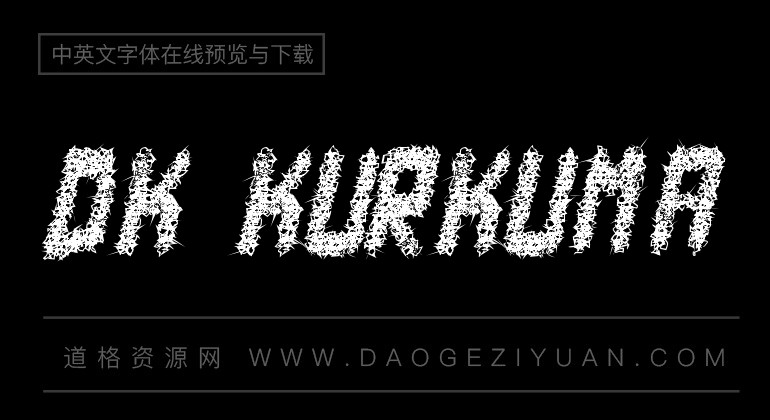
DK Kurkuma
? DK Kurkuma 是一款源自印度的抽象笔画字体,由设计师 Dinesh Kumar 创作。字体的特点是抽象的笔画,结合了中国的山水画和印度的图腾图案,给人以深刻的印象。字体采用了精细的细节设计,使用了鲜艳的色彩,给人以时尚现代的感觉。它具有良好的可读性、优美的外形和丰富的表现力,可以用于设计海报、书籍封面、网站标志、广告牌等。
DK Kurkuma是一款非常不错的手写艺术字体,具有很好的视觉感,适合于文化类的宣传设计、商业类品牌的广告和产品包装设计以及个性化文字排版等较多场景。